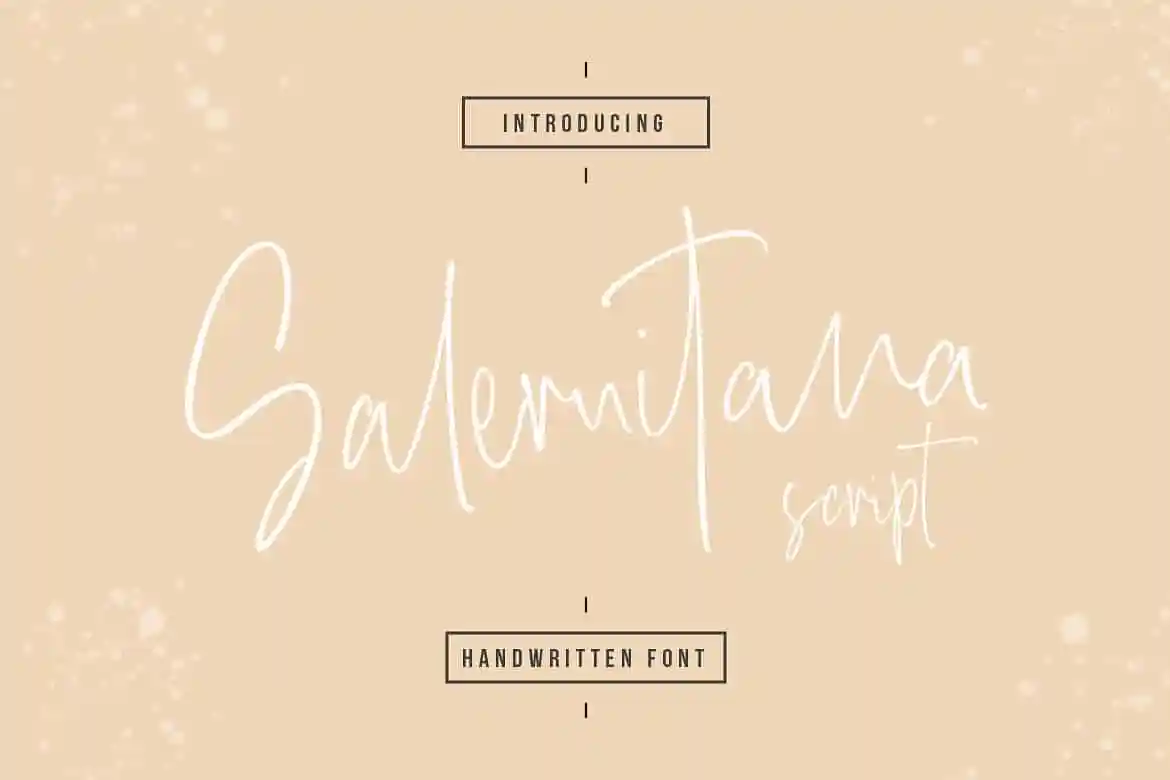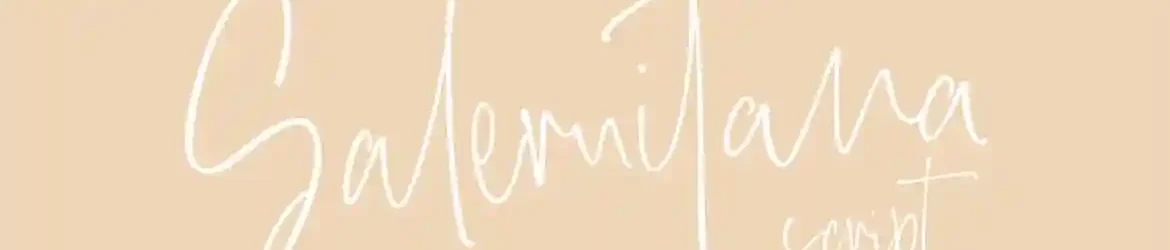
Salernitana Script Font – Download Grátis
Olá a todos! Estamos ansiosos para apresentar à vocês Salernitana Script Font, uma elegante fonte de estilo script que oferece muitas opções para personalizar seu texto com um aspecto natural e autêntico, sem repetições desnecessárias. Este design contínuo e sofisticado está inspirado no estilo delicado e irregular da escrita a mão, oferecendo uma combinação perfeita de elegância e frescor contemporâneo. Salernitana Script é ideal para projetos de marca, designs de móveis de casa, embalagens de produtos – ou até mesmo como um toque de texto estilizado sobretudo no fundo das imagens de imagem. É uma escolha perfeita se você está procurando uma fonte incrivelmente atraente e versátil que deixará sua marca digital mais atraente e única. Não hesite em explorar as possibilidades criativas desta fonte.